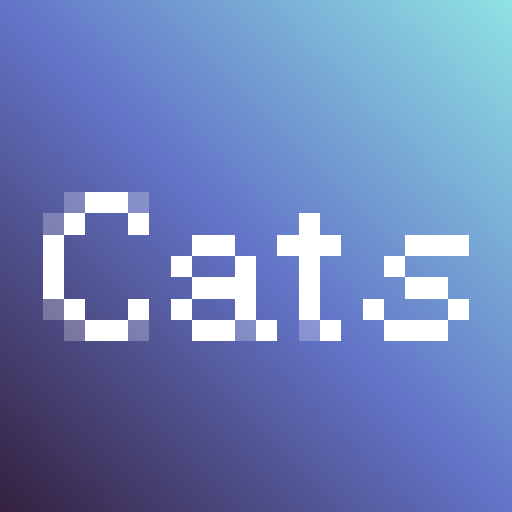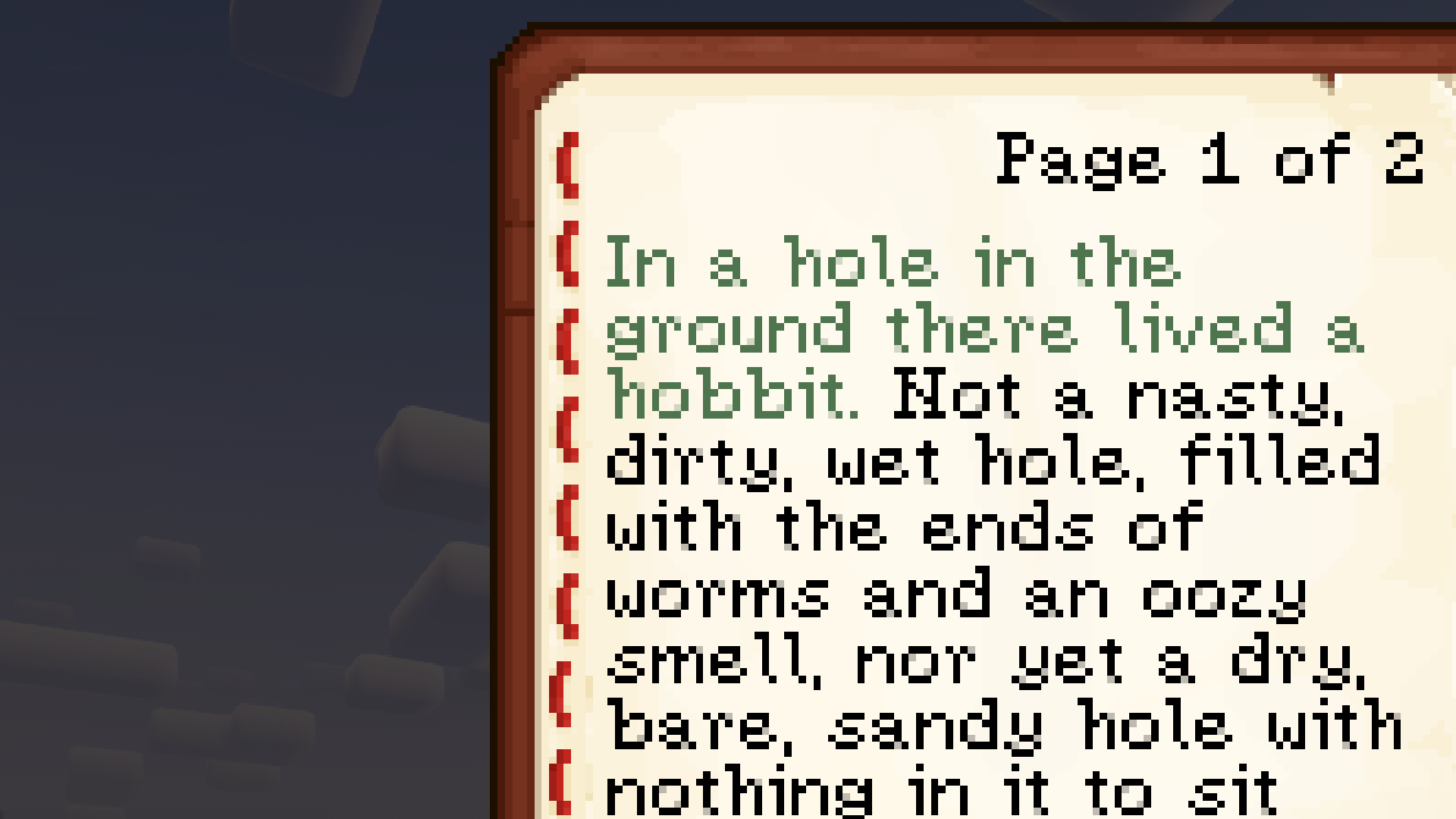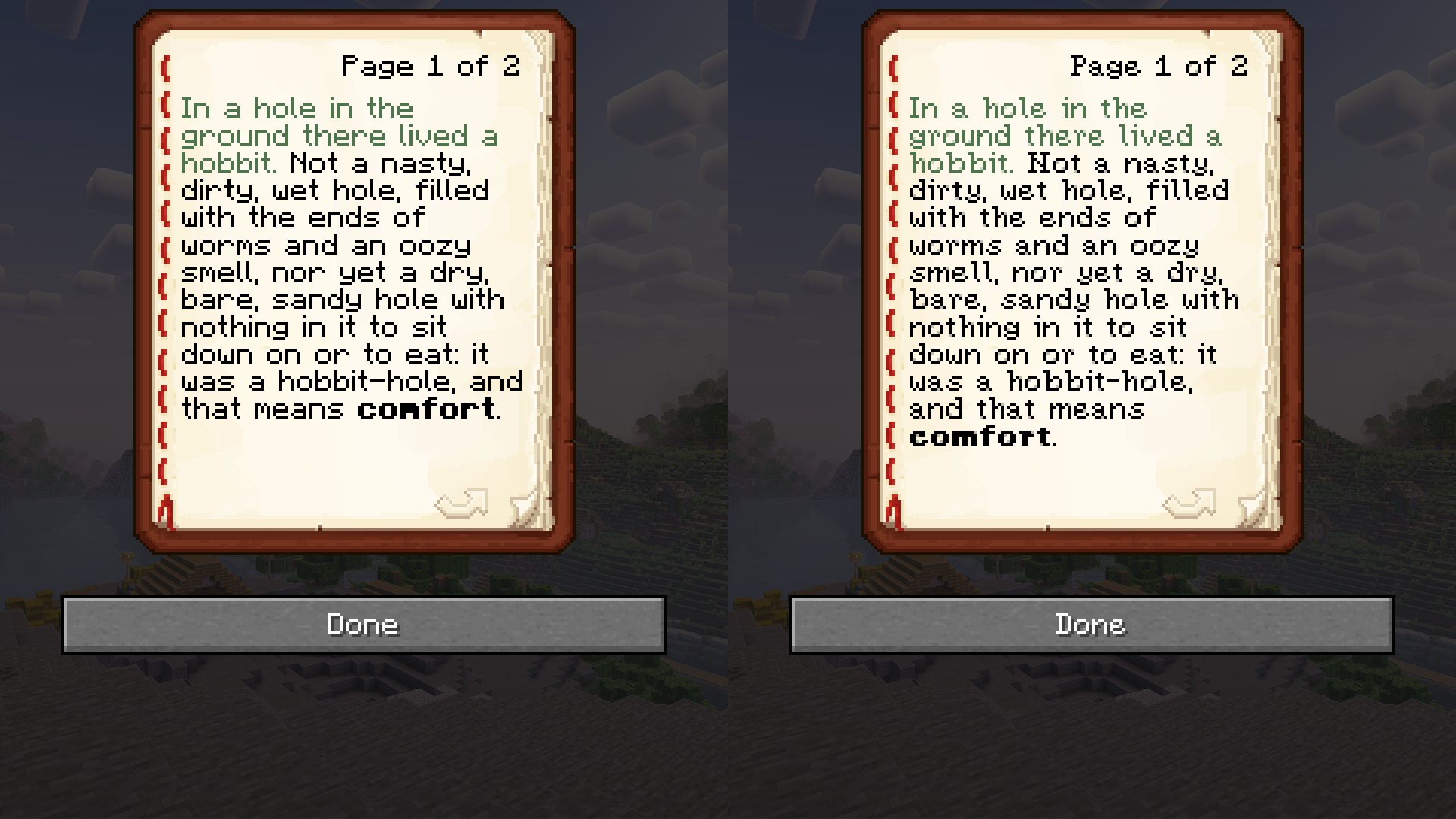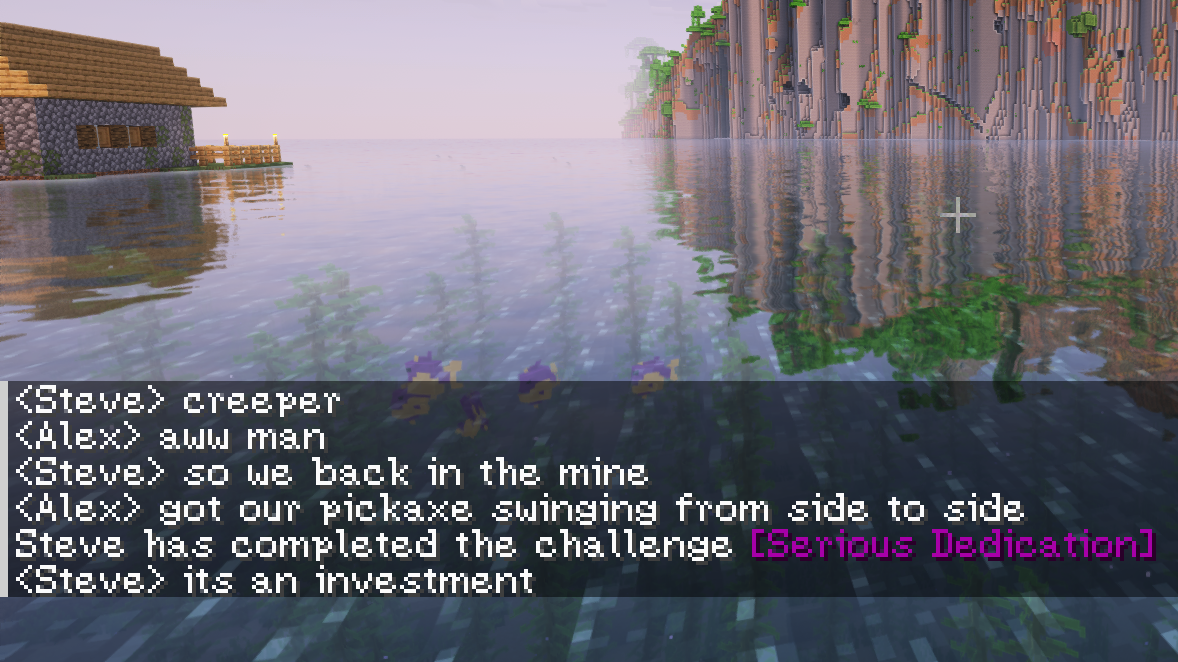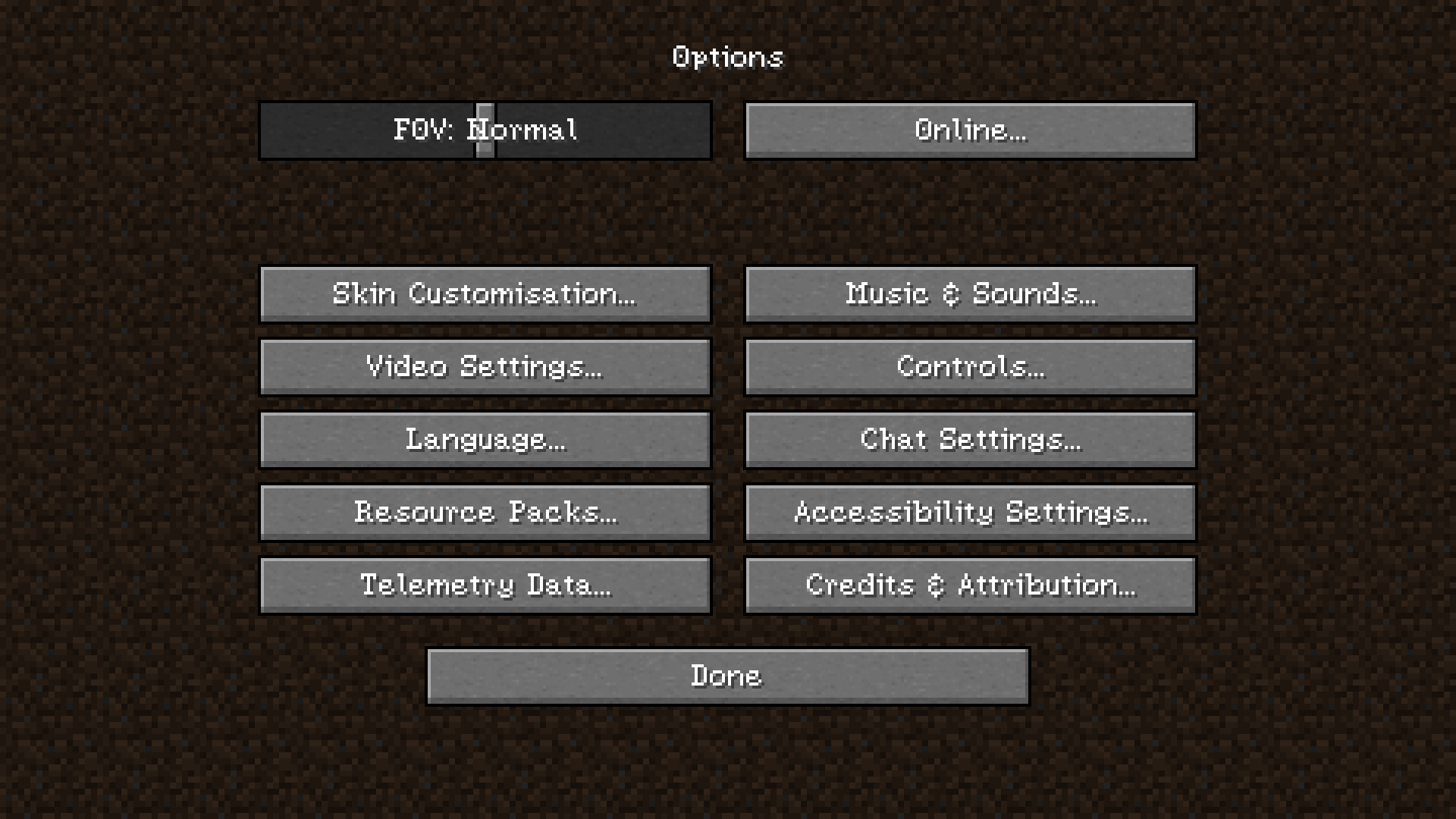
Fantasy Font Pack для Minecraft: новый взгляд на текст в игре
Minecraft — это игра, где каждая деталь может изменить атмосферу. Если вы хотите придать тексту в игре более средневековый и фэнтезийный стиль, то Fantasy Font Pack — отличное решение! Этот ресурспак перерабатывает шрифт, делая его более читаемым и атмосферным.
🔮 Особенности Fantasy Font Pack
Этот пакет предлагает:
✔ Фэнтезийный стиль — шрифт выглядит так, будто взят из старинной книги.
✔ Улучшенная читаемость — буквы стали мягче и естественнее.
✔ Полупрозрачные пиксели — уникальная техника сглаживания, которая редко встречается в других ресурспаках.
⚠ Важно: Пакет пока не поддерживает диакритические знаки (например, буквы с ударениями), но автор обещает добавить их в будущем.
Fantasy Font Pack — отличный выбор для тех, кто хочет добавить в Minecraft больше атмосферы средневековья и фэнтези. Уникальный шрифт, плавное сглаживание и стильный дизайн делают его одним из лучших в своем роде.